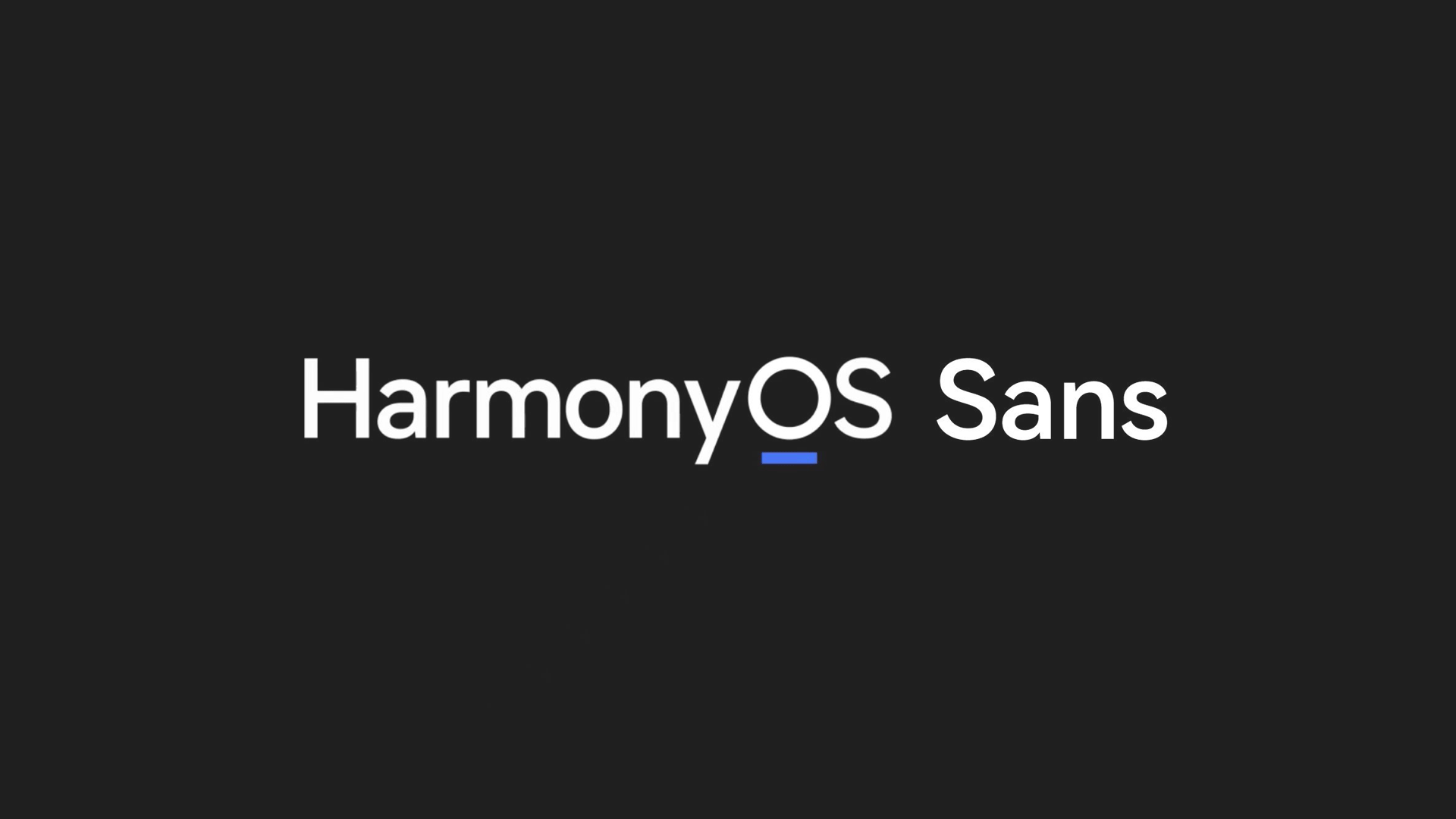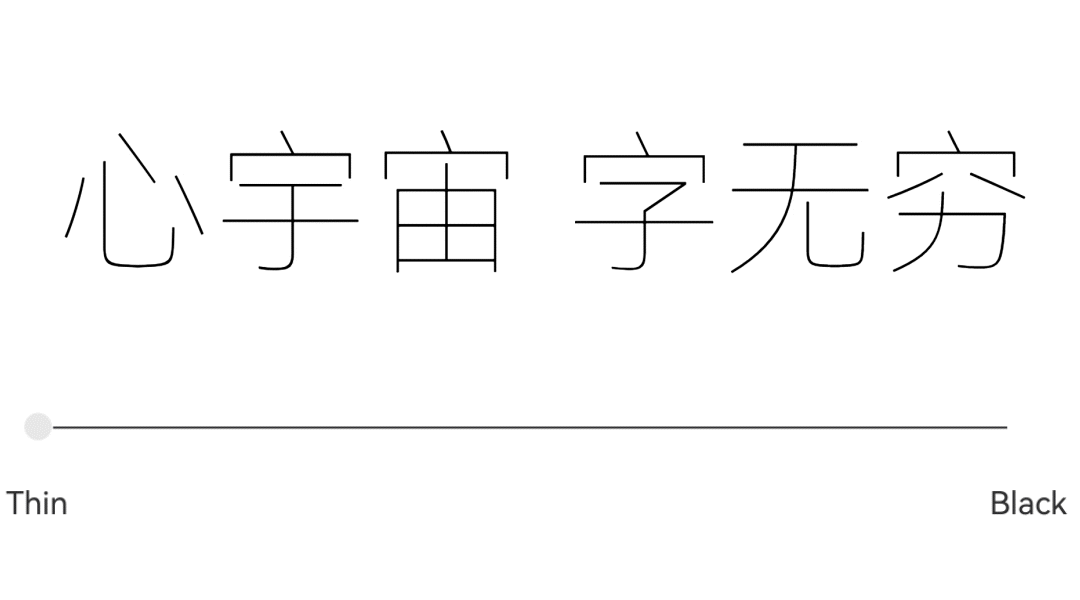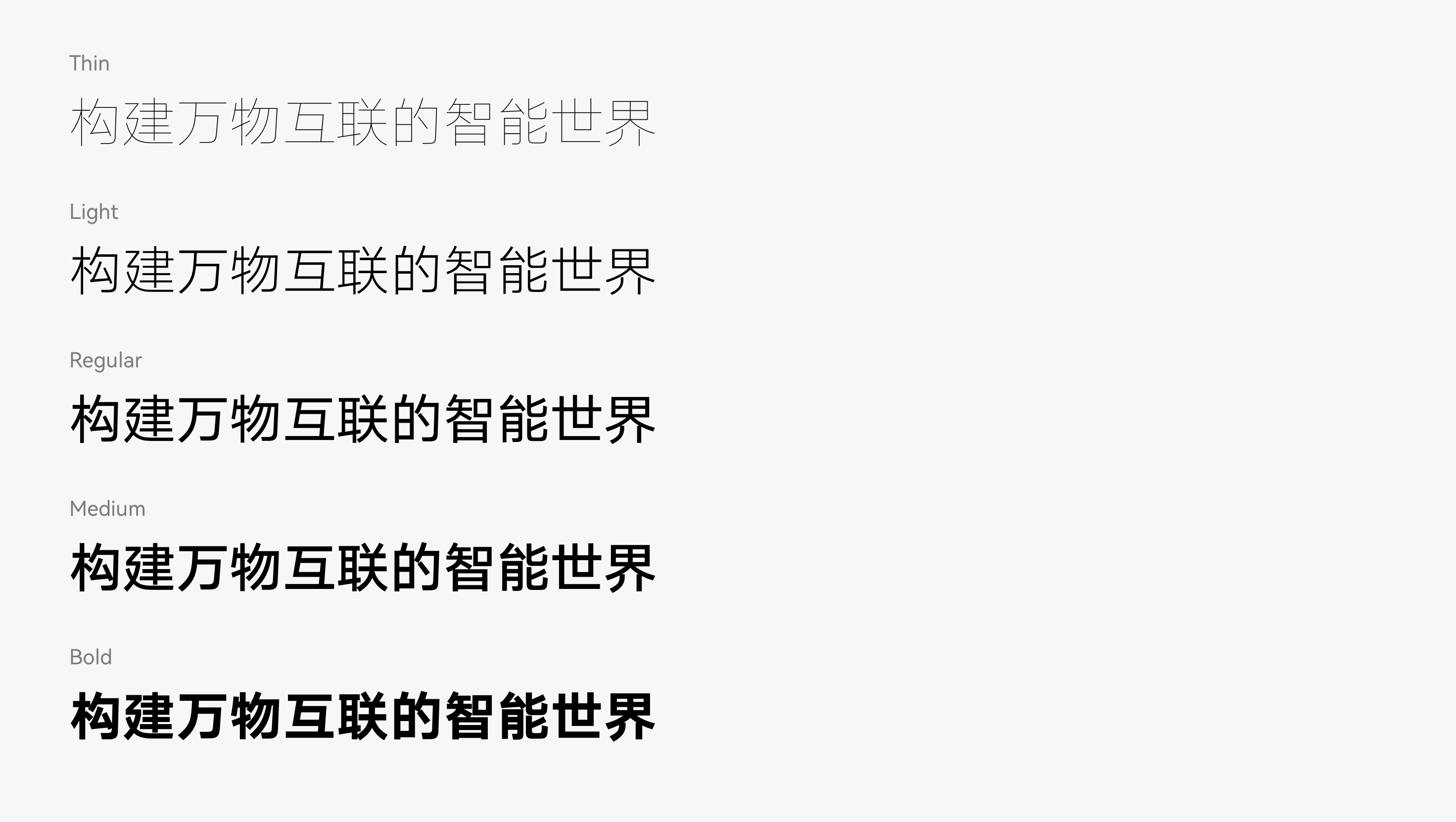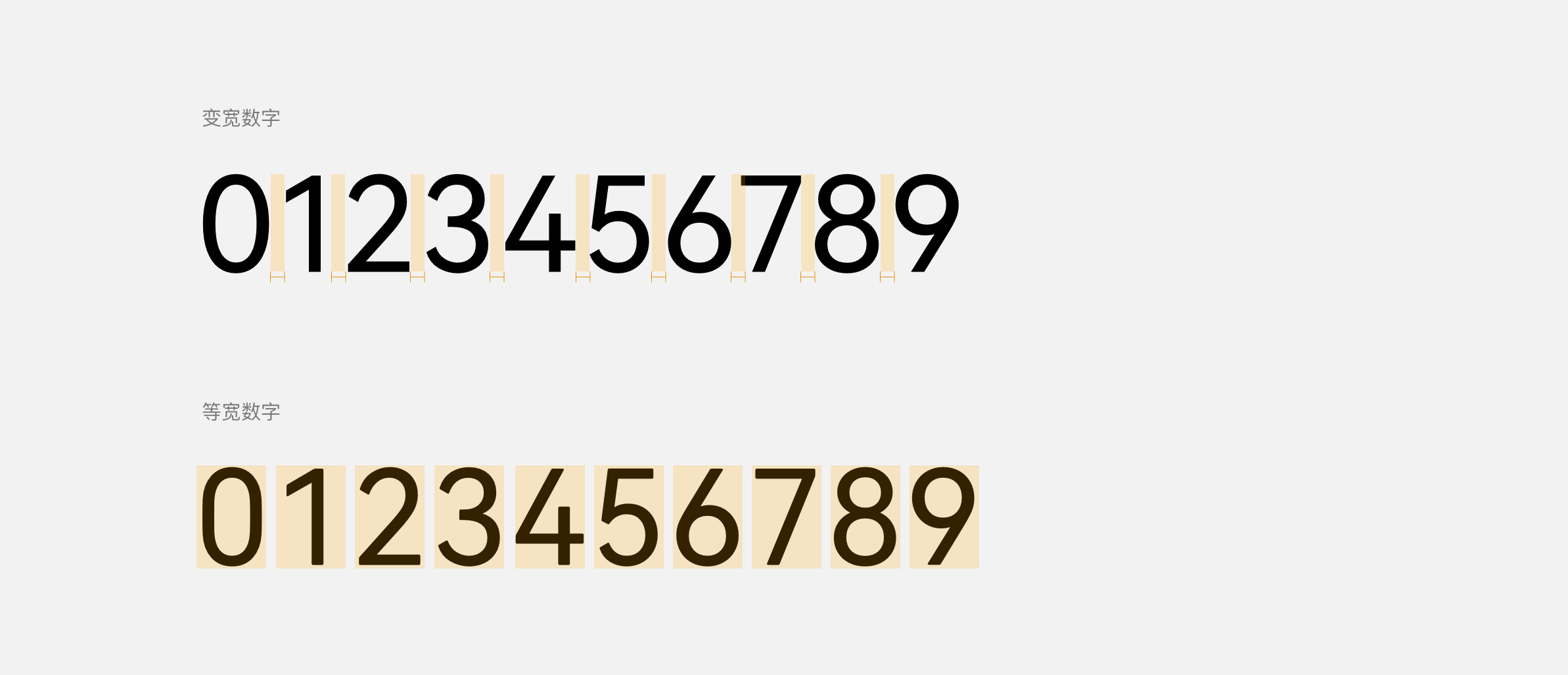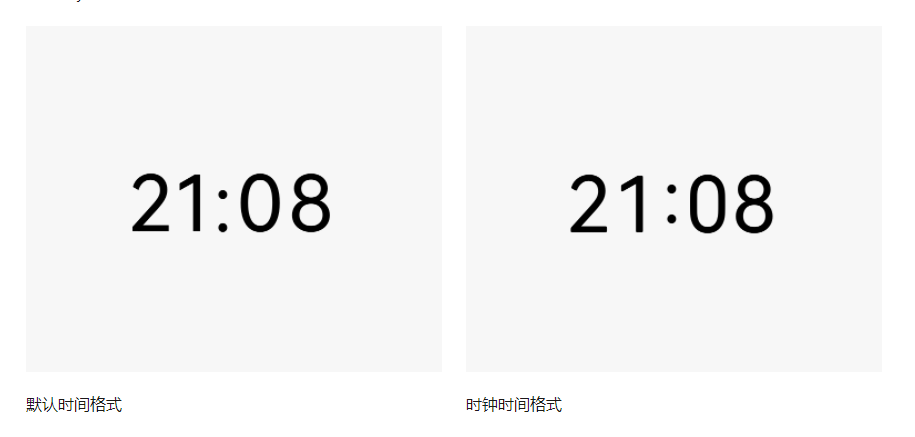
华为定制字体 HarmonyOS Sans(鸿蒙字体)介绍
基于华为全球化视野,以及多元复杂的应用场景,汉仪字库设计的华为全新品牌定制字体 HarmonyOS Sans (鸿蒙)于2021年6月8日正式发布上线。HarmonyOS Sans的设计聚焦字体的功能性和普适性,呈现出这样一款多语言的无级可变字体。字体包含简繁中文、拉丁、西里尔、希腊、阿拉伯等5大书写系统,105种语言。
HarmonyOS 字体特性 · 动态字重粗细调节
HarmonyOS Sans支持可变特性,让用户选择他们喜欢的字体粗细来进行文本的显示。
HarmonyOS 字体特性·支持更多字重能力
HarmonyOS Sans增加了Thin、Light、Bold、Black的字重能力,开发者可以选择需要的字重来构建界面的信息层级。
HarmonyOS 字体特性 ·   等宽与变宽数字字体
HarmonyOS Sans支持变宽和等宽两种样式。文本混排中使用系统默认的变宽数字,在阅读文本段落中能让阅读体验更加连贯。而等宽时钟数字在需要强调数值以及数据需要经常变化的表格和时钟数字的场景中使用时,可以保持数字字宽的对齐,同时更具图形化的呈现可以在界面中脱颖而出。
HarmonyOS 字体特性 ·   支持时钟字体特性
HarmonyOS Sans支持时钟字体特性,冒号格式会根据时间格式自动调整位置。